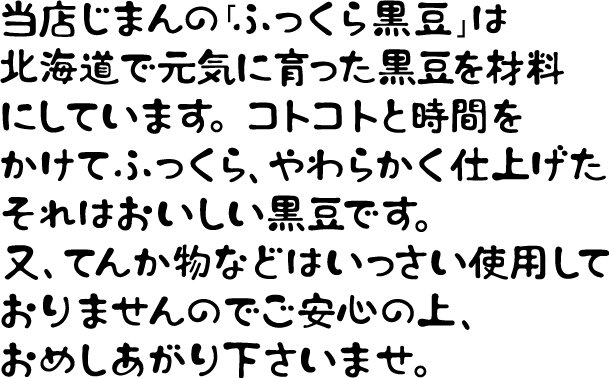
茶太郎の文字見本
ただいま制作中の書体「茶太郎」です。
手描きの雰囲気を残すため、文字のサイズは揃えてありません。また、文字の線幅もいろいろです。もともと揃えていないので、部分的な文字の拡大、縮小に耐えます。
字並び、文字の組み合わせなど、お好みのバランスでお使いいただけます。もちろんそのままでも使えます。
「て」「焼」「せ」拡大。
字間を詰め、文字の並びを少し上下させました。
「わ」「れ」拡大。 「の」「さ」縮小。
字間を詰め、文字の並びを少し上下させました。
「ゆ」「湯」「旅」拡大。 「の」縮小。
字間を詰め、文字の並びを少し上下させました。
字間を少し詰めてあります。
この書体が「茶太郎」です。Illustrator・Fontgrapher・漢字エディットキット等で制作中です。